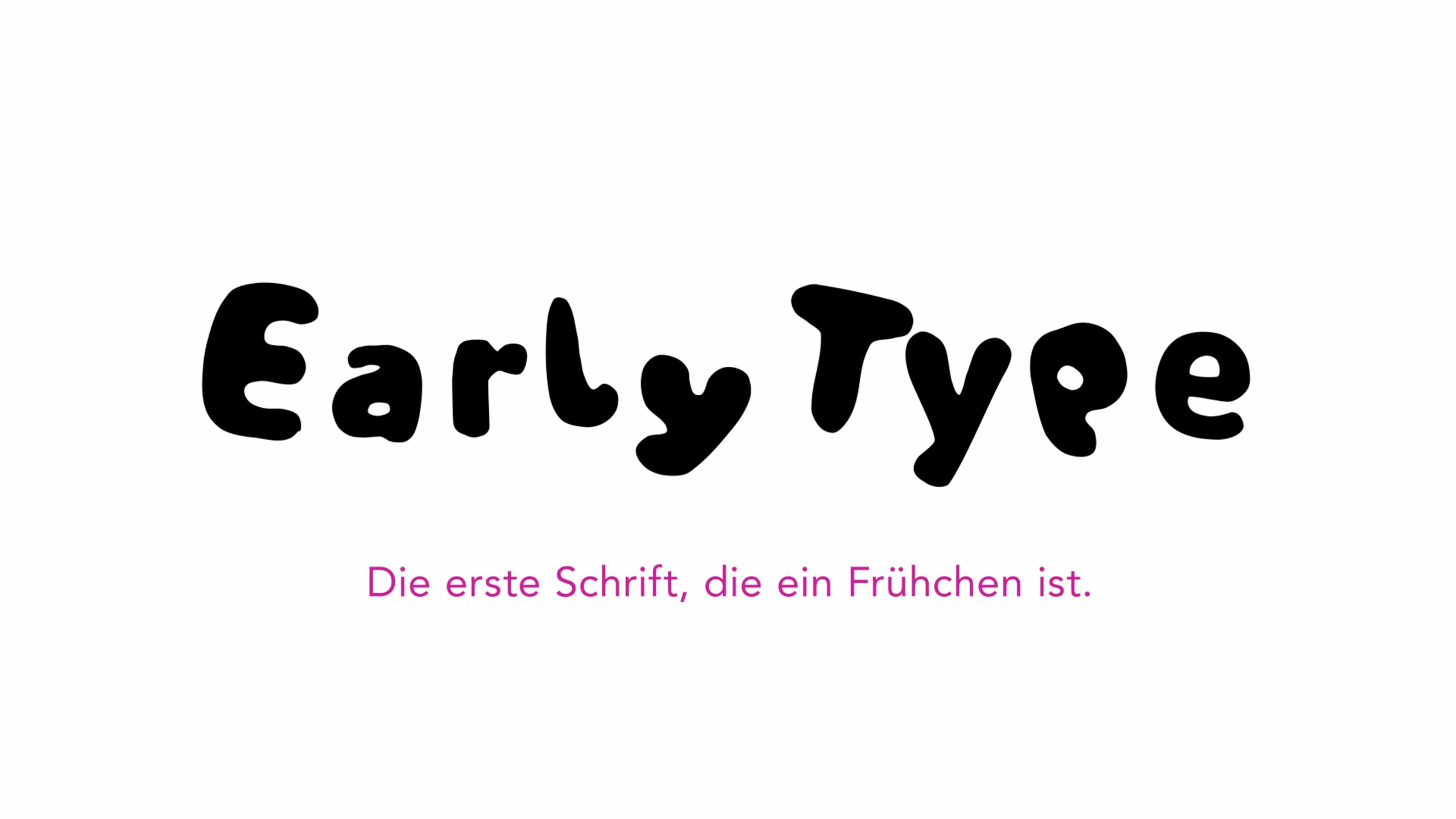
Agentur Kolle Rebbe entwickelt besondere Schriftart „Early Type“
Starkes Zeichen zum Welt-Frühgeborenen-Tag
Early Type
Die Agentur Kolle Rebbe entwickelt mit „Early Type“ eine Schriftart, die ein Frühchen ist. Für die aufwändig gestaltete Schrift wurden die Entwicklungsstadien eines Kindes in die von Buchstaben übersetzt. 40 Schwangerschaftswochen wurden zu 40 Schriftschnitten.
„Die Entwicklung einer Eizelle zum Säugling ist ein echtes Wunder“, erklärt Thomas Knüwer, verantwortlicher Kreativer bei Kolle Rebbe. „Wir wollten auf einfache und überraschende Weise zeigen, wie es sich anfühlt, wenn diese Entwicklung nicht ganz vollendet wird.“ Denn jeder Buchstabe kam per Zufall zwischen der 23. und der 37. Woche zur Welt. Unfertig und zu früh – genau wie ein Frühchen.
Jedes zehnte Neugeborene ist ein Frühchen. Damit sind sie die größte Kinderpatientengruppe in Deutschland. Gerade ihre Familien benötigen von Anfang an umfassende und langfristige Unterstützung. Genau dafür setzt sich der Bundesverband „Das frühgeborene Kind“ e.V. seit mehr als 25 Jahren ein. Am 17. November 2018, dem Welt- Frühgeborenen-Tag, startete der Verband deshalb gemeinsam mit Kolle Rebbe einen ganz besonderen Spendenaufruf.
Spenden-Aktion wird mit Partner-Websites zum großen Erfolg
Am 17. November haben zahlreiche Partner die außergewöhnliche Schriftart auf ihren Websites eingebunden: ihre Headlines erschienen plötzlich im Schrifttyp Early Type. User wurden so auf ungewöhnliche Art auf die Aktion aufmerksam und bekamen die Möglichkeit, direkt zu spenden.
„Die Idee verbindet Emotionalität mit Kreativität – damit hat unser Aufruf nachhaltig Wirkung gezeigt“, freut sich Barbara Mitschdörfer, Vorsitzende des Bundesverbandes „Das frühgeborene Kind“ e.V. Die Summe der Spenden am Welt-Frühgeborenen-Tag war um 10.500% höher als der tägliche Durchschnitt dieses Jahres. Die Reichweite der Facebook- Page des Verbandes konnte um mehr als 700% gesteigert werden und die Seitenaufrufe haben sich um mehr als 60% erhöht.